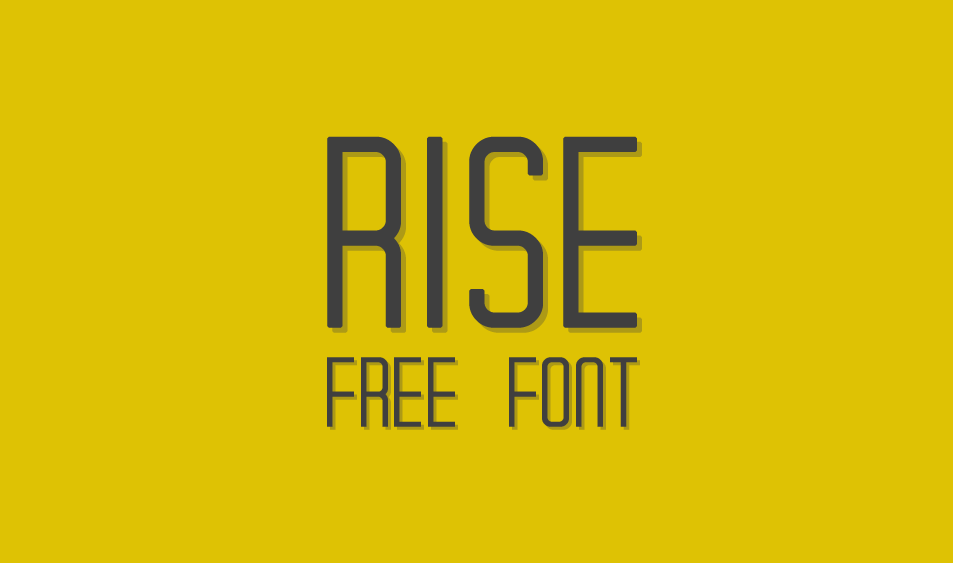
A fonte RISE Typeface é uma escolha ótima para criar designs modernos e clean, ideal para a sua próxima peça visual. Desenvolvida pelo designer Hamilton, essa tipografia sem serif traz clareza e simplicidade às suas mensagens. Seja ela em um logotipo minimalista ou em texto de newsletter, RISE oferece linhas leves e espaçadas que se destacam com facilidade na página. Suas linhas uniformes proporcionam um layout agradável ao olhar, garantindo que seu design seja fácil de ler e memorável. Este é o tipo perfeito para quem busca uma fonte moderna e clara para comunicar ideias de forma precisa e eficaz.